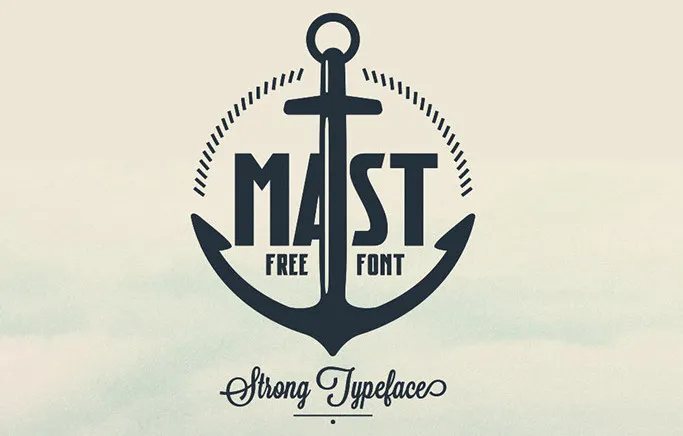
Mast Typeface – Fonte Grátis
Mast Typeface
Introduzimos a Mast Typeface! Esta fonte de tipo sans serif foi projetada por NACH OH!. Com um estilo geométrico e caracteres tipográficos influenciados pelo modernismo e era industrial, Mast conta com um design cuidadosamente otimizado para ambientes digitais pequenos. Seu manual ajustamento de pontos torna-a perfeita para criar templates criativos e post-it de papelão. Através de seu aprimoramento para diferentes tamanhos e aplicações, a Mast Typeface se adapta perfeitamente aos designs modernos e limpos, logos, headlines e banners, além de ser ótima para templates. Ideal tanto para uso em websites quanto nas aplicações móveis, Mast é uma escolha ideal para quem busca um visual minimalista e moderno em seus projetos gráficos.